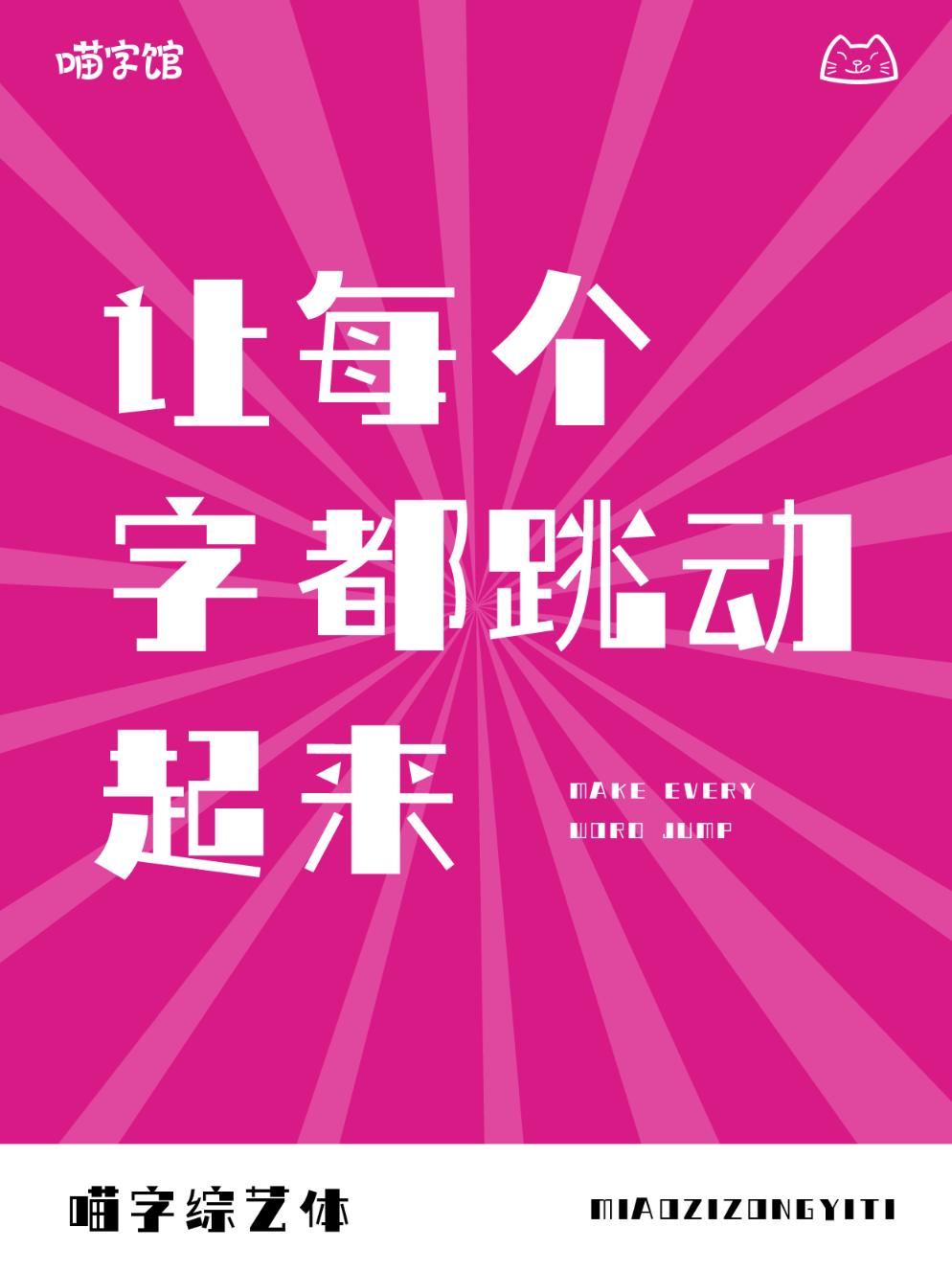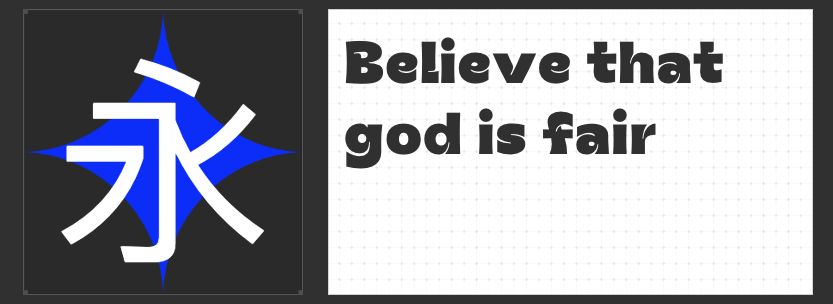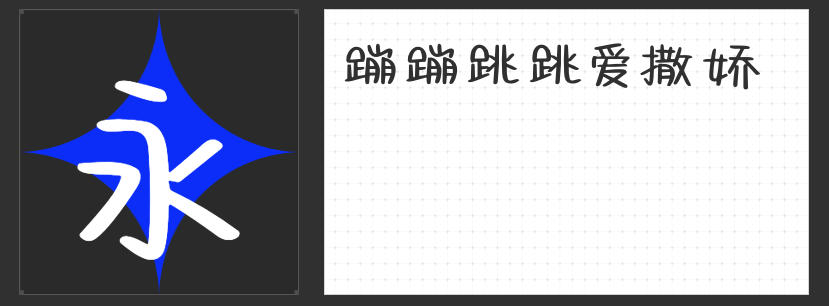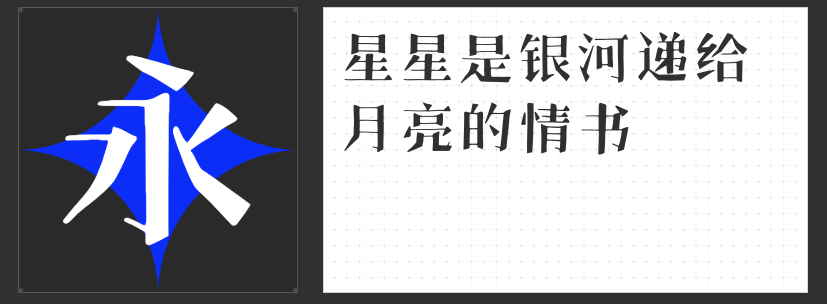
绘本灵魂之窗:探索故事中的梦幻字体
在绘本的奇妙世界里,字体的选择如同绘制色彩斑斓的画布,为故事增添了无限的层次与情感深度。今天,我将为大家推荐几款适合用于绘本设计的字体,它们各具特色,能够为绘本设计带来不一样的视觉享受。
1. 高手庆科手绘宋
这款字体以其温暖而细腻的笔触,仿佛每一笔都蕴含着画家的情感与温度。这款字体适用于描绘温馨、怀旧的绘本故事,它能够完美融合手绘插图的风格,营造出一种时光静好的氛围,让读者仿佛置身于旧日时光之中。
2. 喵字综艺体
拥有活泼可爱的形态,成为了儿童绘本中的宠儿。这款字体模仿了猫咪的憨态可掬,每一个字都像是会跳跃的小精灵,为故事增添了无尽的趣味与活力。它适用于讲述动物冒险、童话故事等充满想象力的内容,能够迅速吸引孩子们的注意力。
3. 高手兵克稚趣体
其圆润饱满的字形和童趣十足的设计,成为了传递纯真与快乐的使者。高手兵克稚趣体在绘本设计中常被用来标注角色对话、旁白或是标题,其独特的风格能够瞬间拉近与读者的距离,让人感受到一股温暖而亲切的气息。
对于想要营造活泼、趣味氛围的绘本,高手兵克Vanguard Regular则是一个不错的选择。这款字体是英文字体,更适合用于使用英文的绘本。它适用于描绘卡通角色、动物世界或充满想象力的奇幻故事,能够激发孩子们的阅读兴趣,并让他们在轻松愉快的氛围中享受阅读的乐趣。
无论是追求现代简洁风格、温馨亲切氛围还是个性创意表达的故事,这些字体都能为绘本的设计提供丰富的选择。它们不仅是文字的载体,更是情感的传递者,能够引领读者走进一个又一个精彩纷呈的故事世界。